ฟอนต์มีผล! จิตวิทยาเลือกฟอนต์สร้างแบรนด์ SME ให้น่าเชื่อถือ
การเลือกรูปแบบตัวอักษร หรือ ฟอนต์ สำหรับธุรกิจอาจดูเหมือนเป็นเพียงรายละเอียดเล็กน้อย แต่ในความเป็นจริงแล้ว ฟอนต์มีบทบาทสำคัญอย่างยิ่งในการสื่อสารตัวตนของแบรนด์และสร้างการรับรู้ในใจของผู้บริโภค มันคือองค์ประกอบเงียบที่ส่งผลกระทบอย่างมหาศาลต่อความรู้สึกและความน่าเชื่อถือที่ลูกค้ามีต่อธุรกิจขนาดกลางและขนาดย่อม (SME)
ประเด็นสำคัญที่คุณจะได้เรียนรู้
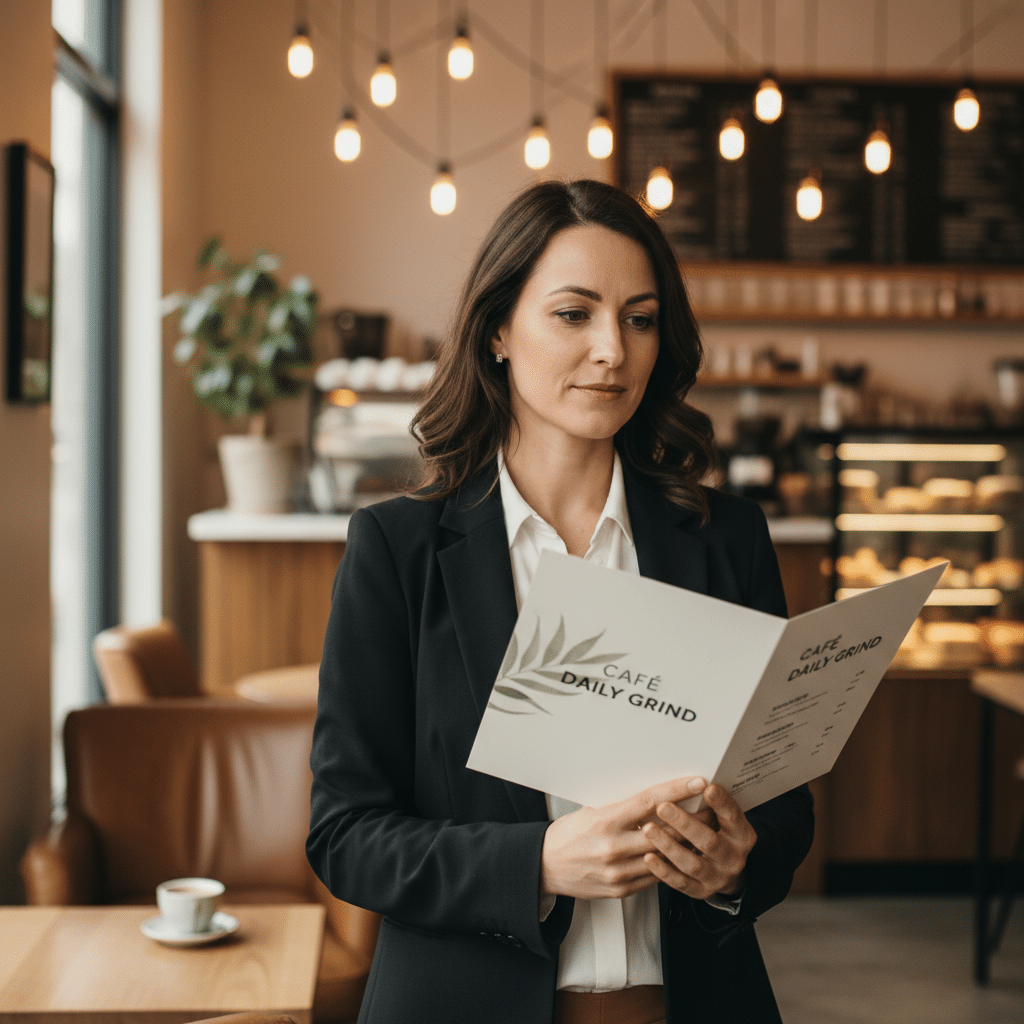
- ฟอนต์คือ “เสียง” ของแบรนด์: ฟอนต์ทำหน้าที่สื่อสารบุคลิกภาพ ค่านิยม และอารมณ์ของแบรนด์ไปยังผู้บริโภคโดยตรง ซึ่งมีผลต่อการสร้างความไว้วางใจและการตัดสินใจซื้อ
- จิตวิทยาเบื้องหลังฟอนต์แต่ละประเภท: ฟอนต์ประเภทต่างๆ เช่น Serif, Sans-serif, Script กระตุ้นอารมณ์และการรับรู้ที่แตกต่างกันอย่างสิ้นเชิง การเลือกใช้จึงต้องสอดคล้องกับสารที่แบรนด์ต้องการสื่อ
- ความสอดคล้องคือกุญแจสำคัญ: การเลือกฟอนต์ต้องเริ่มต้นจากการทำความเข้าใจบุคลิกของแบรนด์และกลุ่มเป้าหมาย เพื่อให้ภาพลักษณ์ที่สื่อออกไปมีความสอดคล้องและน่าเชื่อถือ
- ผลกระทบของการเลือกฟอนต์ผิด: การเลือกฟอนต์ที่ไม่เหมาะสมกับประเภทธุรกิจอาจส่งผลเสียต่อภาพลักษณ์และทำลายความไว้วางใจของลูกค้าได้อย่างไม่น่าเชื่อ
- ความชัดเจนและความสม่ำเสมอ: นอกจากจิตวิทยาแล้ว คุณสมบัติพื้นฐานอย่างความสามารถในการอ่านได้ง่าย (Readability) ในทุกขนาดและแพลตฟอร์ม รวมถึงการใช้งานอย่างสม่ำเสมอ (Consistency) คือปัจจัยสำคัญที่มองข้ามไม่ได้
ฟอนต์มีผล! จิตวิทยาเลือกฟอนต์สร้างแบรนด์ SME ให้น่าเชื่อถือ เป็นมากกว่าเรื่องของความสวยงาม แต่เป็นเครื่องมือเชิงกลยุทธ์ที่ทรงพลังในการสร้างการเชื่อมต่อทางอารมณ์กับลูกค้า ตัวอักษรที่ปรากฏบนโลโก้ เว็บไซต์ นามบัตร หรือเมนูอาหาร ทำหน้าที่เป็น “น้ำเสียง” ของแบรนด์ที่สื่อสารโดยไม่ต้องใช้คำพูด มันสามารถบอกได้ว่าแบรนด์ของคุณมีความเป็นมืออาชีพ ทันสมัย เป็นมิตร หรือหรูหรา การทำความเข้าใจในจิตวิทยาของฟอนต์จึงเป็นสิ่งจำเป็นสำหรับผู้ประกอบการ SME ที่ต้องการสร้างแบรนด์ให้แข็งแกร่งและเป็นที่จดจำในตลาดที่มีการแข่งขันสูง
ทำไมจิตวิทยาฟอนต์จึงเป็นเครื่องมือสำคัญสำหรับ SME
สำหรับธุรกิจ SME ซึ่งอาจมีทรัพยากรจำกัดในการสร้างแบรนด์ การเลือกใช้ฟอนต์อย่างมีกลยุทธ์คือหนึ่งในการลงทุนที่คุ้มค่าที่สุด เพราะฟอนต์เป็นองค์ประกอบพื้นฐานที่ปรากฏอยู่ในทุกจุดสัมผัส (Touchpoint) ระหว่างแบรนด์กับลูกค้า ตั้งแต่ป้ายหน้าร้านไปจนถึงโพสต์บนโซเชียลมีเดีย การเลือกฟอนต์ที่เหมาะสมสามารถสร้างความได้เปรียบได้อย่างมหาศาล
ฟอนต์ไม่ใช่แค่ตัวอักษรที่ถูกออกแบบมาอย่างสวยงาม แต่เป็นเครื่องมือที่ช่วยสร้างภาพลักษณ์ให้ดูเป็นมืออาชีพ สะท้อนตัวตนของแบรนด์ และที่สำคัญคือกระตุ้นความรู้สึกเชิงบวกในใจของลูกค้า การเลือกฟอนต์ที่ถูกต้องสามารถสร้างความน่าเชื่อถือและความไว้วางใจได้ตั้งแต่แรกเห็น ในทางกลับกัน การเลือกฟอนต์ผิดพลาดอาจส่งผลกระทบในทางลบและทำลายความเชื่อมั่นของลูกค้าได้เช่นกัน ลองจินตนาการถึงบริษัทที่ปรึกษาทางการเงินที่ใช้ฟอนต์ลายมือแบบเด็กๆ บนนามบัตร หรือคลินิกทันตกรรมที่ใช้ฟอนต์แบบสยองขวัญบนป้ายร้าน กรณีเหล่านี้แสดงให้เห็นว่าฟอนต์ที่ไม่สอดคล้องกับสาระสำคัญของธุรกิจสามารถสร้างความสับสนและลดทอนความน่าเชื่อถือลงได้อย่างไร
ดังนั้น การทำความเข้าใจจิตวิทยาของฟอนต์จึงเปรียบเสมือนการมีเข็มทิศนำทางให้ผู้ประกอบการ SME สามารถเลือก “น้ำเสียง” ที่เหมาะสมที่สุดสำหรับแบรนด์ของตนเอง เพื่อสื่อสารไปยังกลุ่มเป้าหมายได้อย่างตรงจุดและมีประสิทธิภาพสูงสุด
การวางรากฐานก่อนเลือกฟอนต์
ก่อนที่จะดำดิ่งลงไปในโลกของฟอนต์ประเภทต่างๆ การวางรากฐานที่มั่นคงเป็นสิ่งสำคัญที่สุด กระบวนการนี้จะช่วยให้การตัดสินใจเลือกฟอนต์เป็นไปอย่างมีหลักการและสอดคล้องกับเป้าหมายของแบรนด์
กำหนดบุคลิกภาพของแบรนด์ (Brand Personality)
ขั้นตอนแรกคือการตอบคำถามว่า “ถ้าแบรนด์ของคุณเป็นคน จะมีบุคลิกอย่างไร” แบรนด์ของคุณเป็นแบรนด์ที่สนุกสนานและเป็นมิตร? หรือเป็นแบรนด์ที่หรูหราและสง่างาม? หรืออาจจะเป็นแบรนด์ที่น่าเชื่อถือและมั่นคง? การกำหนดคุณลักษณะเหล่านี้ให้ชัดเจนจะช่วยจำกัดขอบเขตของฟอนต์ที่เหมาะสม เช่น หากต้องการสื่อถึงความน่าเชื่อถือและความเป็นทางการ ฟอนต์ประเภท Serif อาจเป็นตัวเลือกที่ดี ในขณะที่หากต้องการสื่อถึงความทันสมัยและเข้าถึงง่าย ฟอนต์ Sans-serif ก็อาจจะเหมาะสมกว่า
วิเคราะห์กลุ่มเป้าหมายอย่างลึกซึ้ง
หลังจากเข้าใจบุคลิกของแบรนด์แล้ว ขั้นต่อไปคือการทำความเข้าใจกลุ่มเป้าหมายหลัก ทั้งในด้านประชากรศาสตร์ (อายุ เพศ) และจิตวิทยา (ไลฟ์สไตล์ ความสนใจ ค่านิยม) กลุ่มเป้าหมายที่แตกต่างกันมีการตอบสนองต่อฟอนต์ที่แตกต่างกัน ตัวอย่างเช่น กลุ่มวัยรุ่นอาจคุ้นเคยและชื่นชอบฟอนต์ Sans-serif ที่ดูสะอาดตาและทันสมัย ซึ่งมักพบเห็นได้บ่อยในแพลตฟอร์มดิจิทัล ในขณะที่กลุ่มผู้บริหารหรือลูกค้าองค์กรอาจรู้สึกเชื่อมั่นในฟอนต์ Serif ที่ให้ความรู้สึกเป็นทางการและมั่นคงมากกว่า การเลือกฟอนต์ที่สอดคล้องกับความคาดหวังของกลุ่มเป้าหมายจะช่วยสร้างการเชื่อมต่อที่แข็งแกร่งยิ่งขึ้น
คุณสมบัติที่ขาดไม่ได้ของฟอนต์ที่ดี
นอกเหนือจากบุคลิกและกลุ่มเป้าหมายแล้ว ฟอนต์ที่ดีสำหรับแบรนด์ต้องมีคุณสมบัติพื้นฐานที่สำคัญดังนี้:
- อ่านง่าย (Readability): ฟอนต์ต้องสามารถอ่านได้ง่ายในทุกขนาดและทุกสื่อ ไม่ว่าจะเป็นบนหน้าจอคอมพิวเตอร์, โทรศัพท์มือถือ, นามบัตร หรือป้ายโฆษณาขนาดใหญ่
- ชัดเจน (Clarity): ตัวอักษรแต่ละตัวควรมีความชัดเจน ไม่ซับซ้อนหรือคลุมเครือจนทำให้ผู้อ่านต้องพยายามเดา
- สม่ำเสมอ (Consistency): ควรเลือกใช้ฟอนต์หลักและฟอนต์รองไม่เกิน 2-3 แบบ และใช้มันอย่างสม่ำเสมอในทุกสื่อของแบรนด์เพื่อสร้างภาพจำที่ชัดเจน
- น่าเชื่อถือ (Trustworthiness): ฟอนต์ต้องสะท้อนถึงความเป็นมืออาชีพและสร้างความไว้วางใจให้กับแบรนด์
- เข้ากันได้ดี (Compatibility): ฟอนต์ที่เลือกต้องทำงานร่วมกับองค์ประกอบอื่นๆ ของแบรนด์ เช่น โลโก้ สี และรูปภาพ ได้อย่างลงตัว
เจาะลึกประเภทฟอนต์และพลังทางจิตวิทยา
ฟอนต์สามารถแบ่งออกได้เป็นหลายประเภท แต่ละประเภทมีลักษณะเฉพาะตัวและกระตุ้นการรับรู้ทางอารมณ์ที่แตกต่างกัน การทำความเข้าใจจิตวิทยาเบื้องหลังฟอนต์กลุ่มหลักๆ จะช่วยให้ผู้ประกอบการ SME สามารถเลือกใช้ได้อย่างเหมาะสมกับบริบทของธุรกิจ